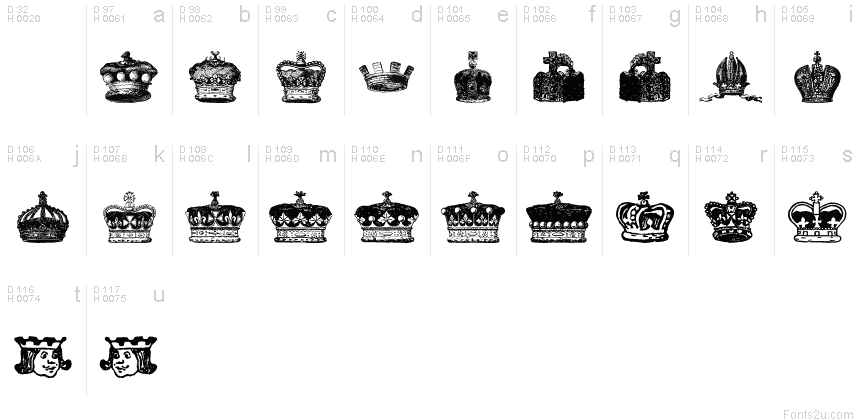
Шрифт Crowns and Coronets от Steven J. Lundeen (Emerald City Fontwerks) — это бесплатный дингбат-шрифт, который превращает каждое нажатие клавиши в богато прорисованный королевский символ. Каждая корона выглядит так, словно сошла со старинной гравюры: плотная штриховка, крошечные жемчужины, острые металлические грани и бархатные подушечки — всё в глубоком черном цвете. Текстуры восхитительно несовершенны, придавая вашим макетам налет подлинного винтажного оттиска, в отличие от плоских современных наборов иконок.
Используя Crowns and Coronets, вы можете мгновенно добавить торжественный акцент приглашениям, обложкам книг, геральдическим логотипам, сертификатам, игровым интерфейсам, упаковке или историческим инфографикам. Стабильная толщина линий и высокая детализация делают эти символы достаточно мощными для печатей и значков, но при этом достаточно изящными для рамок и разделителей при использовании в малом кегле. Этот бесплатный шрифт отлично сочетается с четким антиквенным или гротескным шрифтом в верхнем регистре, позволяя украшенным коронам выступать в качестве ярких декоративных якорей в вашем дизайне.